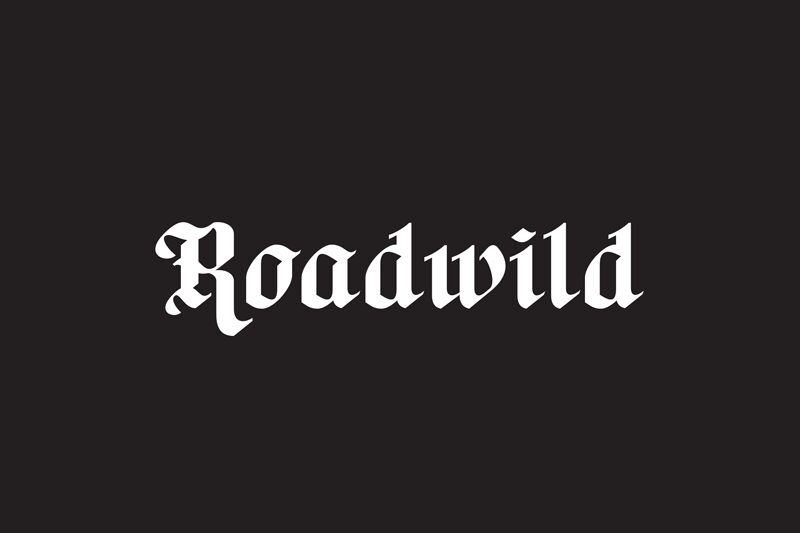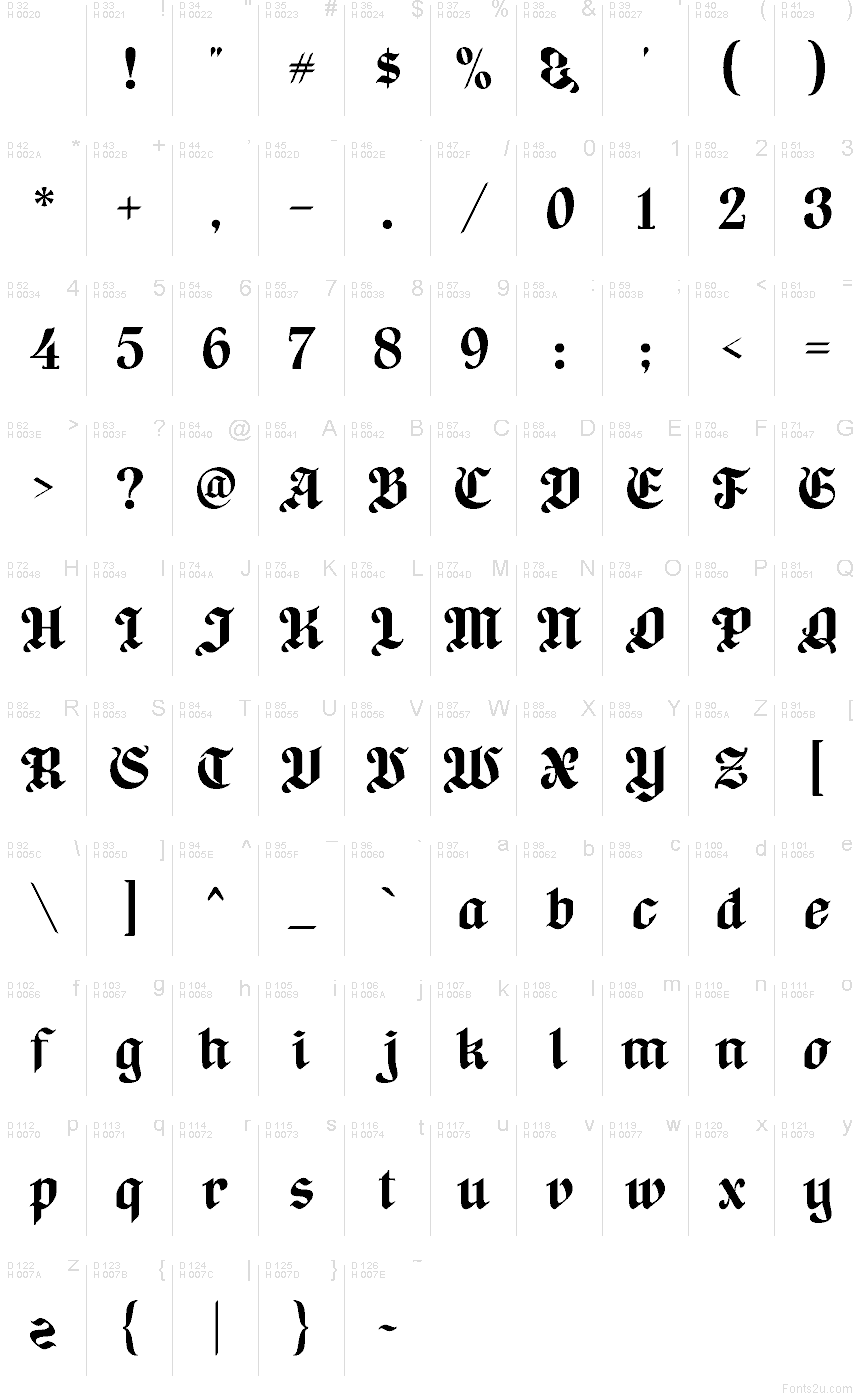
Road Wild od studia YP7 je bezplatné středověké gotické písmo s hustým, tesaným rytmem připomínajícím staré nápisy blackletter. Písmena stojí na ostrých lomených křivkách a háčkovitých ozdobách, což písmu dodává drsný, starosvětský nádech, který působí spíše pouličním než ceremoniálním dojmem.
Díky tomu je skvělou volbou pro obaly alb, branding hospod, plakáty, názvy her a grafiku na oblečení, kde trocha syrovosti pomůže sdělení vyniknout. Jako bezplatné písmo se hodí pro krátké názvy, výrazné titulky a logotypy, zejména pokud hledáte tuto těžkou gotickou texturu, aniž byste sklouzli k přílišné zdobnosti.